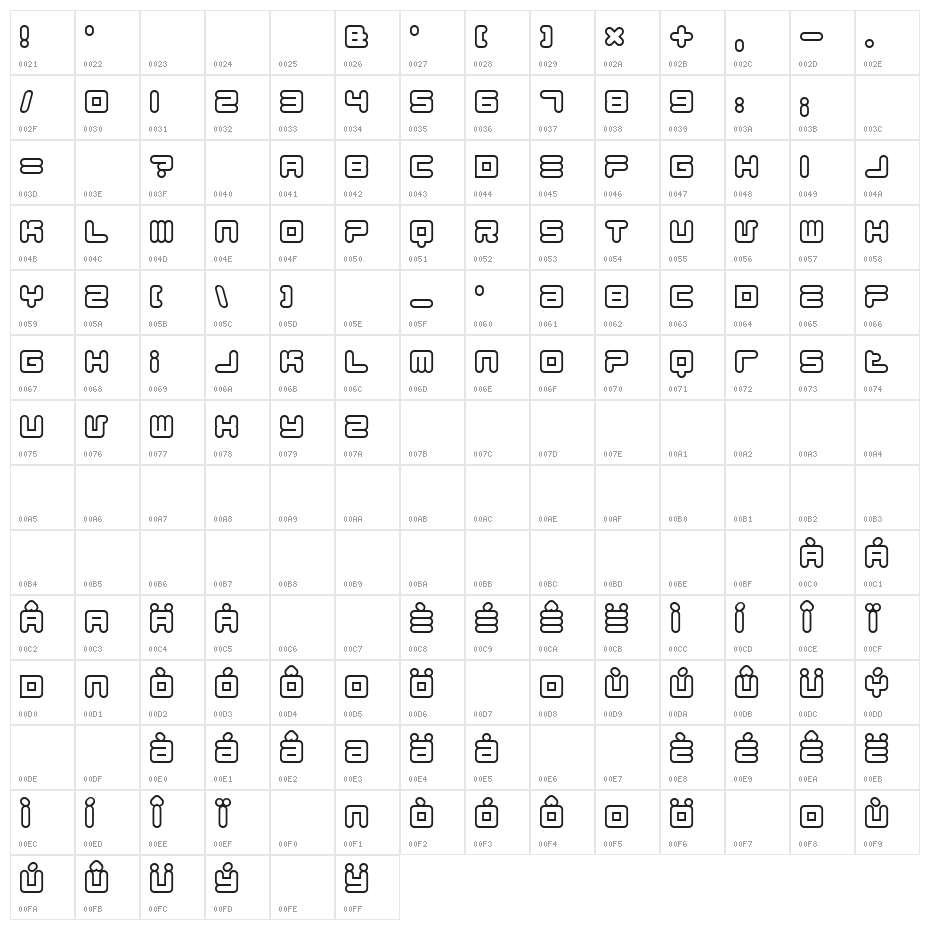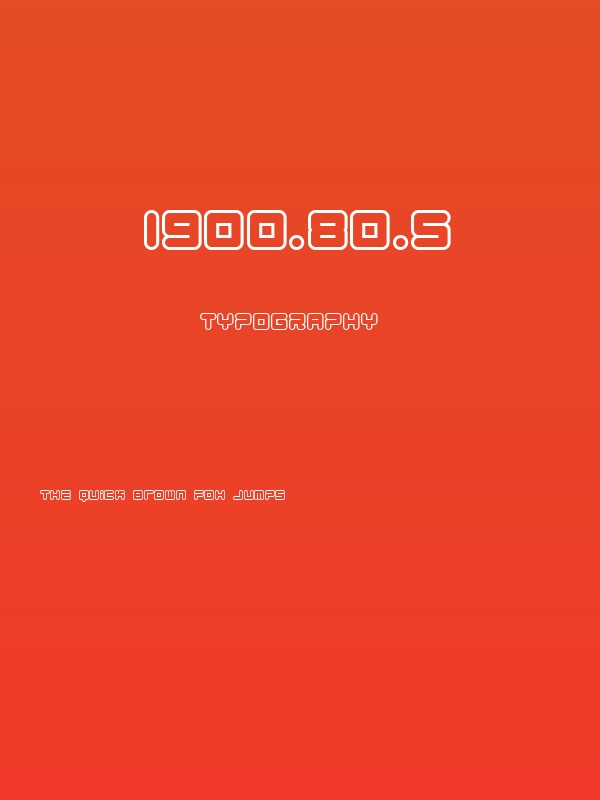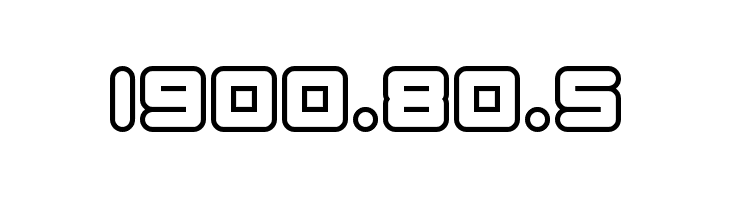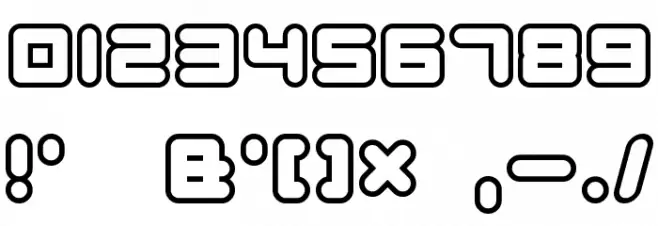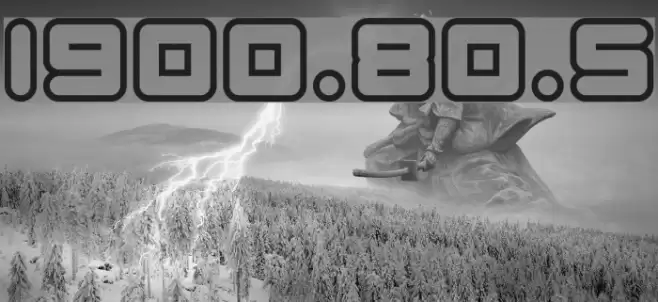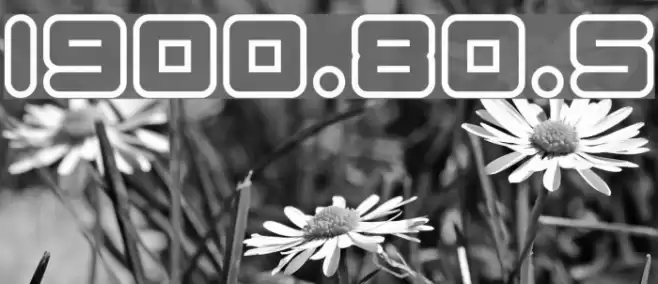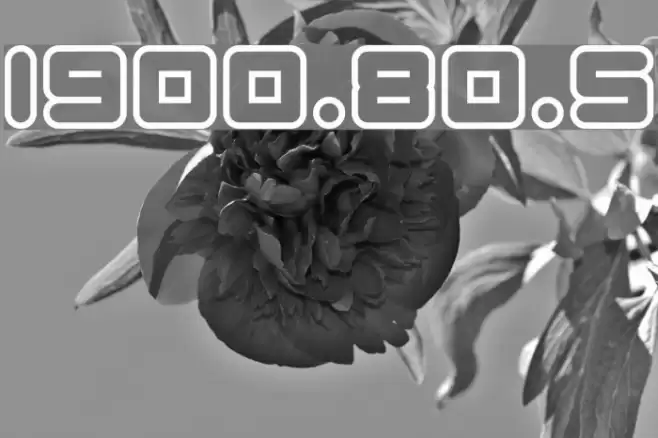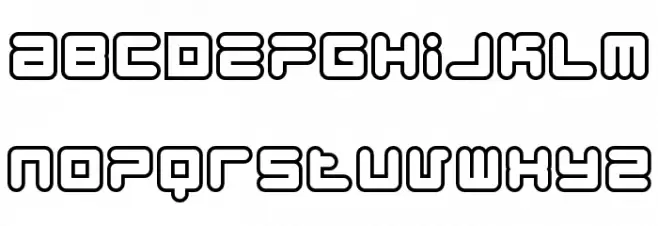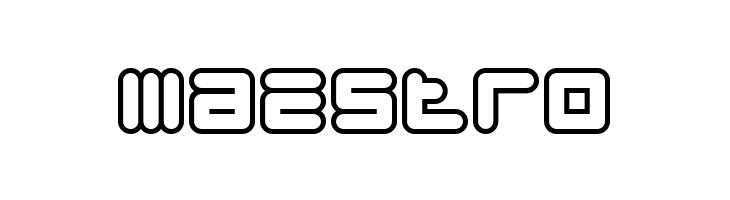
1900.80.5 Font
Fonts by dustBUST - Andreas Nylin
| Projets proposés | Ideal for use in children's books, video game titles, posters, and branding for tech or entertainment industries. |